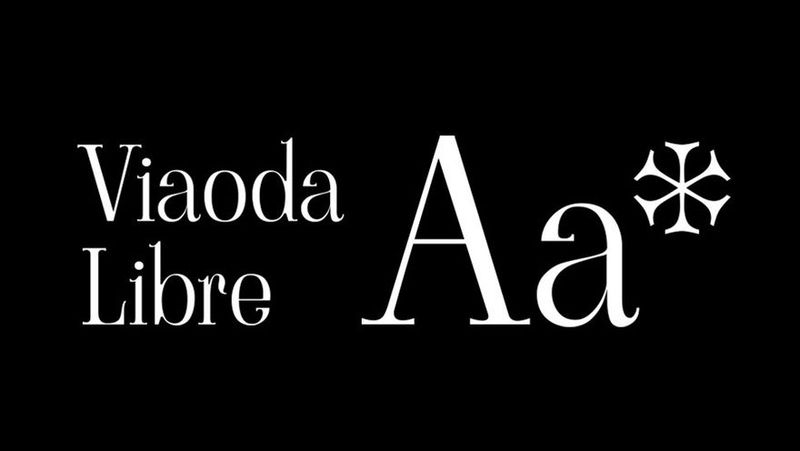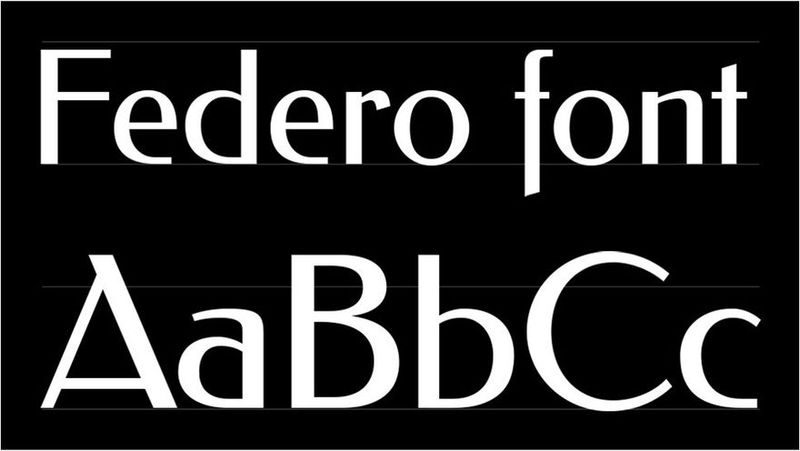
Типографика – это искусство, обладающее художественными, эстетическими и техническими ценностями, поэтому она заслуживает большего внимания, чем обычно ему уделяет широкая публика. Мы настолько привыкли видеть текст повсюду, что почти никогда не останавливаемся, чтобы взглянуть на эти буквы, на то, как они созданы и расположены, и, что особенно важно, как они вписываются в дизайн и взаимодействуют с графическим контекстом, в который они помещены.
Мы, в Qode Interactive, считаем, что к типографике следует подходить с таким же вниманием, как и к любому другому элементу дизайна. Дело не только в том, что шрифты «несут» текст, они также наполняют дизайн определенными психологическими ценностями и передают определенные сообщения, подобно изображениям и цветам. Одни шрифты выражают энергию и оптимизм, другие придают дизайну элегантность или изысканность, третьи романтичны, и, конечно же, существует множество профессиональных и довольно строгих гарнитур. Правильный выбор шрифта обеспечивает согласованность дизайна, а также чрезвычайно важен с точки зрения брендинга и создания эстетической индивидуальности.
Несмотря на то, что существует так много удивительных инди-словолитней создающих всевозможные инновационные и классические шрифты, дизайнеры часто выбирают бесплатные шрифты, которые можно скачать в Интернете. В наши дни существует масса мест, где дизайнер может скачать шрифт, но сегодня мы хотим поговорить о нашем (и всеми) любимом – Google Fonts.
Есть много причин, по которым Google Fonts доминирует над другими бесплатными источниками шрифтов. Во-первых, это Google, и вы знаете, что они очень серьезно относятся ко всему. С Google Fonts дизайнер может быть уверен, что будут учтены все технические детали, например, лицензирование, и их легко добавить на любой сайт благодаря API Google Fonts. Кроме того, Google Fonts представляет собой тщательно подобранную коллекцию шрифтов, которые были проверены, опробованы и протестированы перед размещением их в репозитории. Речь идет о высококачественных шрифтах, которые отлично работают на экранах любого типа и размера. Беда только в том, что их так много, что сложно выбрать. Фактически, вам доступно более 1200 бесплатных семейств шрифтов (и их число продолжает расти, поскольку Google регулярно добавляет новые), поэтому поиск подходящего вашему проекту шрифта может оказаться сложной задачей.
Из-за этого, а также из-за того, что мы действительно увлечены типографикой, мы решили поделиться подборкой, по нашему мнению, самых интересных шрифтов Google на данный момент.
Krona One
Мы начинаем наш список с превосходного шрифта Krona One, созданного талантливым типографом Ивонн Шюттлер. Это малоконтрастный шрифт без засечек и один из немногих истинно полурасширенных стилей (хотя, мы рассматриваем его как полностью расширенный) в репозитории Google Fonts. Вдохновленный рукописным шрифтом шведских плакатов начала 20-го века, Krona One несет в себе отчетливую атмосферу скандинавского ретро, но на самом деле может соответствовать широкому спектру различных стилей и эстетики. Легко читаемый, просторный и яркий, Krona One – отличный выбор для заголовков или любого текста, который вы хотите сделать жирным и заметным. Тем не менее, это не значит, что его нельзя использовать и для более мелкого текста. Что мы и сделали в нашей теме Gracey, где Krona One используется для hero-типографики, а также для меню заголовка. Мы также сочли этот шрифт отличным выбором для демо Art Festival в теме Stockholm, где мы использовали как меньшие, так и большие стили Krona One.
Syne
Еще один шрифт, нашедший широкое применение в наших темах, Syne был впервые разработан в 2017 году в качестве пользовательского шрифта для художественного фестиваля Synesthésie в Сен-Дени. Концепция шрифта была придумана французской дизайн-студией Bonjour Monde, а спроектировал его Лукас Дескруа при участии Армана Мохтаджи. Syne выпускается в пяти различных стилях: regular, medium, semi-bold, bold и extra bold. Начало этой семье шрифтов, разумеется, положил regular стиль – прекрасный геометрический шрифт без засечек, удобный и подходящий для самого широкого применения, от заголовков до небольших фрагментов текста. Тем не менее, для тех, кто хочет заявить о себе более смело в своих заголовках, студия заказала дополнительные стили, каждый из которых тяжелее предыдущего и увенчан забавным, широким extra bold стилем. Micdrop – одна из наших тем, в которой более жирные стили Syne используются для создания особенно узнаваемого характера с легким намеком на ретро-эстетику. Некоторые домашние страницы тем, например, Label Showcase, используют только Syne, не комбинируя его с другими шрифтами, что показывает, насколько универсальным и практичным является этот шрифт, несмотря на его довольно громкий характер. Мы также выбрали Syne для нашей темы Laurits, где мы исследовали более мягкую сторону этого шрифта, который также очень хорошо сочетается с геометрическим, секционным макетом.
Italiana
Как следует из названия, Italiana – это шрифт без засечек, в значительной степени вдохновленный итальянской типографической традицией, в первую очередь рукописными стилями. Разработанный дизайнером Сантьяго Ороско как элегантный, утонченный шрифт с крохотной долей эстетики dolce vita, Italiana был в первую очередь предназначен для заголовков, напоминающих буквы, использовавшиеся в газетах и журналах начала 20-го века. Italiana в настоящее время доступна только в обычном стиле, но семейство в разработке, поэтому мы надеемся, что скоро появятся дополнения. Это чистый, воздушный и пропорциональный шрифт, а его элегантный характер делает его особенно подходящим для модных и творческих проектов. В отличие от многих других дизайнерских творений, вдохновленных Италией, этот шрифт ни в малейшей степени не является производным и избегает обычных эстетических банальностей. Он легко адаптируется и хорошо вписывается в самые разные стили и контексты, и нам очень понравилось, как он соответствует атмосфере нашей темы Oráiste. Его сочетание тонких и толстых элементов, а также тщательный кернинг и интервалы делают Italiana воздушным, но самобытным шрифтом, который отлично подходит для настроения, которое мы хотели создать с помощью нашей темы.
Bellezza
Как и Italiana, Bellezza черпает вдохновение в итальянской культуре, на этот раз в ее моде. Этот красивый, изысканный женственный шрифт без засечек принадлежит к группе гуманистических шрифтов, заимствованных из старых латинских шрифтов. Благодаря немного большему контрасту между тонкими и широкими штрихами, Bellezza добавляет индивидуальности гуманистическому стилю, а его классические пропорции делают его более читабельным и удобным. Когда мы работали над темой Töbel, Bellezza стала естественным и очевидным выбором. Шрифт с особенно элегантным характером стал отличным средством придания макетам дополнительной нотки изысканности и уникального итальянского шика.
Space Grotesk
Space Grotesk – это шрифт, разработанный чешским дизайнером Флорианом Карстеном на основе шрифта фиксированной ширины Space Mono от Colophon Foundry (также шрифта Google) 2017 года. При создании этого пропорционального шрифта без засечек Карстен хотел сохранить некоторую причудливость шрифта Space Mono, но и сделать его более читабельным. Этот универсальный, адаптируемый шрифт доступен в пяти стилях: light, regular, medium, semi-bold и bold. Он отлично сочетается со своим старшим братом с засечками, Space Mono.
Federo
В 1909 году знаменитый пионер шрифтов без засечек Якоб Эрбар разработал шрифт Feder-Grotesk, который был впервые отлит в 1910 году франкфуртской словолитней Ludwig & Mayer. В 2011 году Олекса Волочай разработал для Cyreal цифровую интерпретацию этого классического шрифта – дисплейный веб-шрифт Federo. Идея заключалась в том, чтобы шрифт оставался близким к оригиналу – подчеркнутый без засечек с заметно неравномерной толщиной штрихов, напоминающий рукописный шрифт, написанный ширококонечным пером, в характерном стиле ар-нуво, но улучшить его, сделать его немного более последовательным. Слегка уменьшена контрастность, исправлены пропорции и увеличены внутрибуквенные просветы, что улучшило читаемость шрифта. В результате получился прекрасный, готовый к использованию в Интернете шрифт с ярко выраженной индивидуальностью и стилем. Нам понравилось демо Animated Showcase, в котором мы решили создать настроение, сочетающее творческий подход и профессионализм.
DM Sans
Многие шрифты, которые вы можете найти в репозитории Google Fonts, на самом деле были заказаны самой Google, как и в случае с DM Sans. Он был разработан Джонни Пинхорном под творческим руководством DeepMind и MultiAdaptor, его выпустили в 2019 году. В его основу легла гарнитура Poppins от Pinhorn. DM Sans – это малоконтрастный геометрический шрифт без засечек, который действительно нравится Google, и обычно он предназначен для текста меньшего размера. DM Sans хорошо сочетается с родственным шрифтом DM Mono, а также с Baskerville, Roboto и Noe. Он доступен в нескольких стилях: regular, medium и bold, с соответствующим курсивом. DM Sans поддерживает расширенный набор латиницы, а значит подходит для английского и большинства других западно-европейских языков.
DM Sans, безусловно, является одним из наших фаворитов на все времена, и мы использовали его для ряда тем, например, Zermatt, где он хорошо сочетается с бруталистскими и швейцарскими дизайнерскими акцентами. Мы также использовали DM Sans для нашей многоконцептуальной темы Stockholm, и, совсем недавно, для Qi Theme, нашей первой в мире бесплатной темы WordPress. DM Sans также был выбран для плагина Qi Addons for Elementor. Наш выбор был продиктован тем, что это чистый, очень разборчивый шрифт с ярко выраженным современным характером, возможно, в большей степени, чем некоторые другие высококачественные шрифты, широко используемые в Интернете. В связи с тем, что многие дизайны смещаются в сторону стандартов доступности с более крупными шрифтами, шрифт DM Sans, простой, малоконтрастный и широкий, особенно хорошо соответствует этим стандартам.
Caudex
Первоначально созданный в конце 1990-х годов, Caudex – это шрифт с засечками, который позже был адаптирован для Интернета с помощью FontForge. Первоначально созданный с использованием стандарта ISO 8859–1 и следуя рекомендациям Medieval Unicode Font Initiative 3.0, Caudex был разработан с целью печати старого рукописного текста. Фактически, его стиль представляет собой современный взгляд на надписи из средневековых манускриптов, а его индивидуальность представляет собой сочетание современной функциональности и классического орнамента. Он имеет два веса – regular и bold, а также соответствующий курсив. Помимо латинских глифов, он также включает греческие буквы. Caudex – это шрифт, который хорошо сочетается со многими шрифтами, как с засечками, так и без. Например, для нашей темы Gaspard, мы использовали его для текста и заголовков и объединили с Italiana для типографики hero-изображения, и с Catamaran для навигационных ссылок, создав элегантный и сбалансированный микс.
Cinzel Decorative
Являясь частью очень популярного семейства веб-шрифтов Cinzel, Cinzel Decorative является отличным выбором для дизайнов, которые хотят передать ощущение элегантности и класса. Этот шрифт с заглавными буквами, созданный Натанаэлем Гамой, следует классическим пропорциям и отличается элегантными росчерками и расширенными штрихами, которые придают ему каллиграфический вид. Это семейство шрифтов было основано на ранних римских надписях, но в современной интерпретации. Благодаря своему классическому характеру, Cinzel Contemporary прекрасно подходит для дизайна, связанного с литературой, искусством и культурой. Он доступен в нескольких стилях, включая extra bold и black. Более сдержанным представителем этого семейства является Cinzel, с теми же классическими пропорциями и стилем, но без завитков. Благодаря своему элегантному характеру, Cinzel стал идеальным выбором для заголовков нашей темы Belletrist, созданной для писателей, издателей и библиотек, где мы соединили его с не менее сложным Cormorant Garamond для абзацев и Open Sans для навигационных ссылок.
Viaoda Libre
Вдохновленный вьетнамским культурным наследием, символикой и письмом, Viaoda Libre – это семейство шрифтов, сочетающее в себе традиции и современность, привнося восхитительный твист в элегантную типографику с засечками. Созданный немецким дизайнером вьетнамского происхождения Gydient (Тра Джианг Нгуен) при участии Вьетаня Нгуена, Viaoda Libre предназначен для личного и коммерческого использования, и одинаково хорошо подходит как для заголовков, так и для меньшего текста. Название «Viaoda» представляет собой комбинацию «Vietnamese» и «Ao Dai» (Аозаи), термина, используемого для обозначения традиционной одежды, которую носят как женщины, так и мужчины. Штрихи шрифта напоминают мягкие плавные линии Аозай, а их общий характер тонкий и изысканный. Это вдохновение также заметно в ярко выраженных лигатурах между символами, таких как «st» и «ft», что делает шрифт таким ярким и узнаваемым. Будучи относительно новым семейством шрифтов, Viaoda Libre продолжает развиваться, и дизайнер надеется, что это добавит ценность вьетнамской культуре во всем мире.
Вывод
Это далеко не полный список наших любимых шрифтов Google на данный момент. Нашим дизайнерам было трудно сузить свой выбор, поскольку в репозитории Google есть так много невероятно хорошо продуманных гарнитур и семейств шрифтов, каждое из которых имеет свой характер и практическое значение. Выбор шрифта для дизайна, как всегда, зависит от множества факторов, среди которых его цель, предполагаемое использование и эстетический характер. При выборе шрифта также важно иметь возможность увидеть его в действии, и именно здесь такие ресурсы, как Fonts in Use, могут оказаться полезными. Мы надеемся, что наш список вдохновил вас на более глубокое погружение в репозиторий Google Fonts, а не использовать стандартные Open Sans, Roboto и Oswald. Множество замечательных, функциональных шрифтов с великолепным дизайном ждут вас и ваш следующий проект. Обязательно сообщите нам о своем открытии в области типографики и поделитесь тем, что вам понравится больше всего.